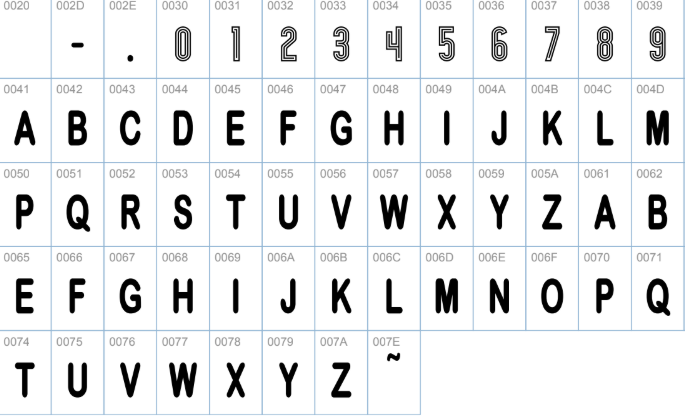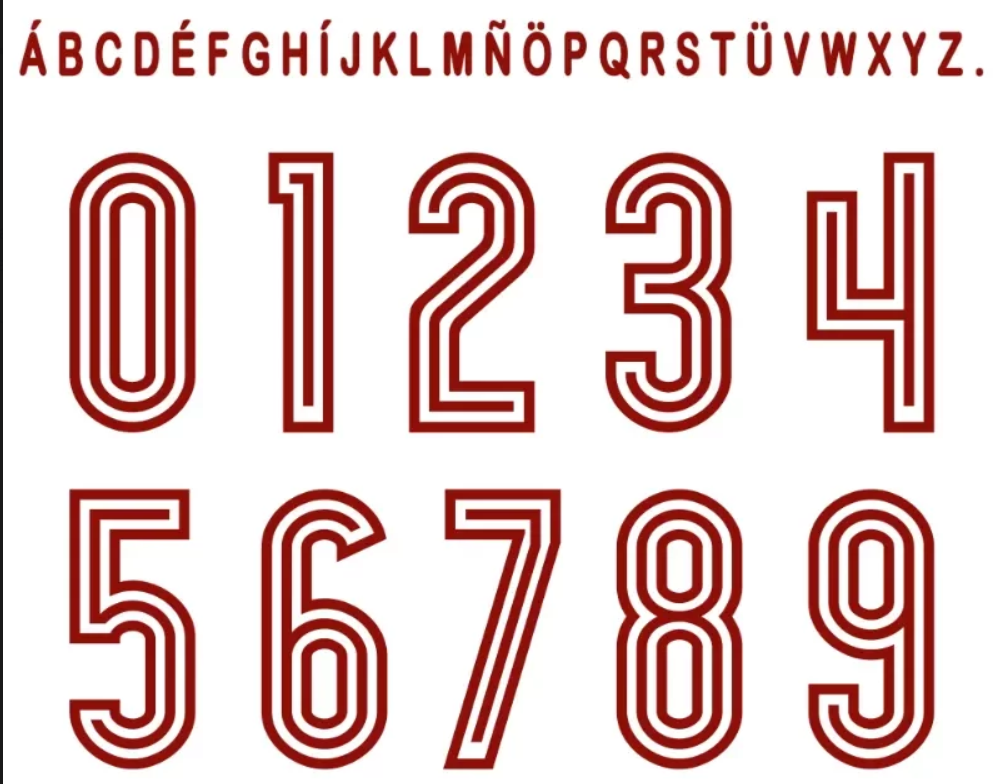
A temporada de 2020 foi marcante para o São Paulo FC, e um dos detalhes que definiram a estética dos uniformes daquele ano foi a tipografia. Sob a assinatura da Adidas, as camisas do Tricolor Paulista apresentaram uma fonte de numeração e nomes limpa, moderna e cheia de personalidade, que imediatamente se tornou objeto de desejo dos designers e torcedores.
- Nome da Fonte: São Paulo 2020 (Variação Adidas)
O Estilo Visual: Modernidade e Legibilidade
A fonte desenvolvida pela Adidas para o São Paulo em 2020 é uma tipografia sans-serif (sem serifa) robusta e geométrica. Ela se destaca pelas suas linhas retas e cortes angulares sutis em algumas letras, o que transmite uma sensação de velocidade e tecnologia.
Diferente de fontes mais arredondadas ou clássicas, este estilo foi pensado para máxima legibilidade, tanto para o torcedor no estádio quanto para a transmissão de TV. É uma fonte imponente, que preenche as costas da camisa com autoridade, e foi usada em todos os uniformes (titular, reserva e alternativo) da temporada 2020-2021.